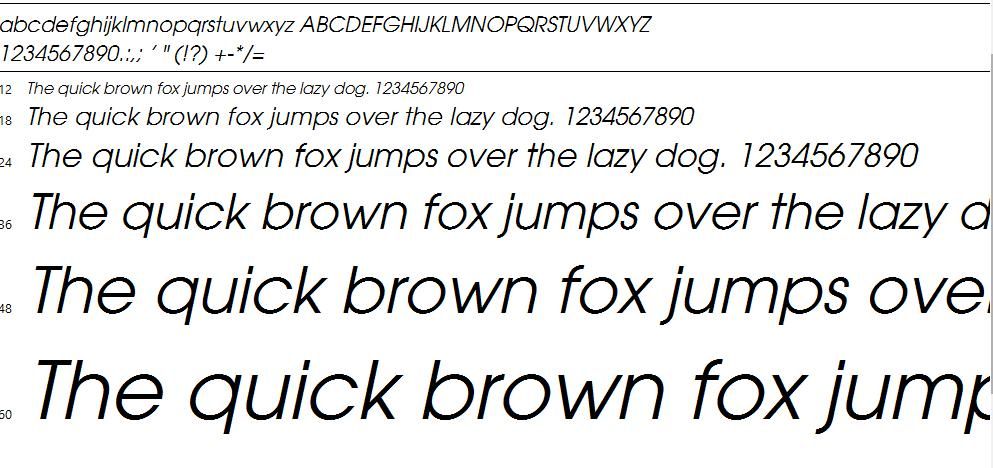
Hệ thống vi tính hay smartphone của bạn tê liệt hoạt động mà thiếu hẳn sự tham gia của phông chữ. Chức năng của phông chữ là tuyệt đối quan trọng, bởi nó trợ giúp cho việc soạn thảo văn bản. Trang trí làm quảng cáo hay bất cứ việc nào khác. Nếu bạn làm việc của người thiết kế đồ họa thì hẳn đã chẳng còn gì xa lạ với font chữ UTM AVO.
Ngoài ra không những quen thân với dân thiết kế mà phông chữ này được sử dụng phổ biến. Cho những ngành nghề khác như thầy cô giáo hay những em học trò. Trong thông tin này mọi người bên nhau tìm hiểu kỹ hơn về bộ font UTM AVO này nhé !
Font UTM AVO là gì?
UTM AVO nằm trong bộ font chữ UTM với rất nhiều kiểu chữ đẹp mắt sử dụng. Cho các công việc đồ họa trên máy tính. Với đặc điểm đẹp mắt kèm 4 kiểu định dạng bao gồm nét mỏng, đậm, in thường và in nghiêng. Font avo hiện nay được rất nhiều người ưa chuộng sử dung. Rõ ràng, đơn giản, không quá cầu kỳ. Chính là một trong những đặc điểm nổi bật làm nên phong cách của font chữ UTM AVO.
Nếu văn bản mà bạn gõ sử dụng trên nền font chữ này. Thì sẽ tạo cảm giác văn bản thật chững chạc và đứng đắn hơn. Điều này rất phù hợp với nghề giáo viên và được các giá viên ưu tiên sử dụng. Đây chính là lý do tại sao font utm còn được gọi là font dành riêng cho giáo viên
Những đặc điểm của font UTM AVO ?
Trong rất nhiều phông chữ đang được ứng dụng thường nhật thì mỗi phông chữ đều có. Những tính năng nổi bật và phòng phương thức đặc biệt nhằm đáp ứng cho một chỗ làm sự khác nhau. Và font UTM AVO cũng không nằm ngoài luật lệ này. Mọi người hãy cùng khám phá xem font UTM AVO có những tính năng nổi trội nào nhé.
Là bộ phông chữ đẹp cho máy vi tính, tương xứng cho các bạn xây dựng hình ảnh. Tạo ra nhiều thông tin mang tính nghệ thuật cao.